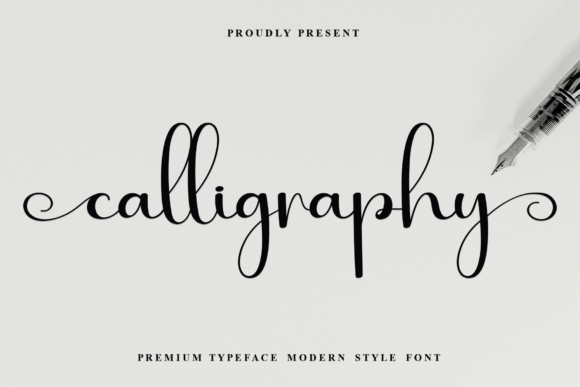
Calligraphy
Calligraphy : La police manuscrite qui séduit les créatifs
Vous recherchez une police qui allie élégance et originalité pour vos projets ? Calligraphy est le choix idéal. Cette police manuscrite, au trait raffiné et aux courbes harmonieuses, apporte une touche sophistiquée qui transforme chaque design en véritable œuvre d’art.
- Un style intemporel : inspirée de la calligraphie traditionnelle, la police conserve une allure classique tout en restant résolument moderne.
- Lisibilité exceptionnelle : chaque caractère est soigneusement équilibré, garantissant une lecture fluide même à petite taille.
- Polyvalence créative : parfaite pour les invitations, les logos, les affiches, les couvertures de livres ou les posts sur les réseaux sociaux.
- Impact visuel garanti : le tracé élégant et les finitions précises attirent l’œil et renforcent le message que vous souhaitez transmettre.
En adoptant Calligraphy, vous donnez immédiatement à vos créations une signature visuelle unique, capable de captiver votre audience et d’ajouter une valeur perçue supérieure à vos projets. Que vous soyez graphiste professionnel, blogueur passionné ou simple amateur de belles polices, laissez-vous séduire par le charme distinctif de Calligraphy et créez des designs spectaculaires qui resteront gravés dans les mémoires.